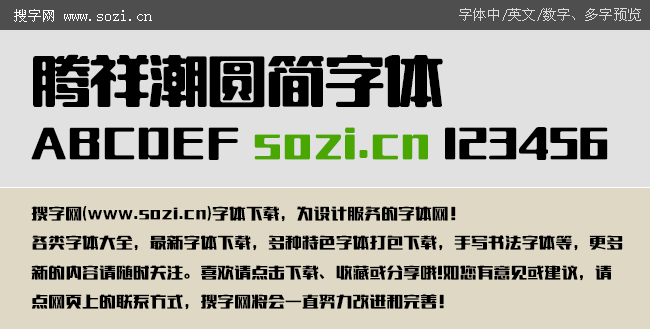
騰祥潮圓簡字體
搜字網(wǎng)提供一款騰祥潮圓簡中文藝術(shù)字體下載,潮圓是一款富于變化的美術(shù)類黑體,是在潮黑的基礎(chǔ)上變換設(shè)計(jì)而成。雖然字形結(jié)構(gòu)與潮黑相同,但兩款字的風(fēng)格氣質(zhì)截然不同。潮圓將潮黑的棱角柔化形成被融化之感,融化了的筆畫圓潤富于親和力。字形結(jié)構(gòu)扁方、端莊,橫豎筆畫粗細(xì)比例適度、豎筆粗壯有力,布白均勻、行文貫通。潮圓筆畫簡潔圓潤細(xì)微處變換靈動,即實(shí)用又富有裝飾效果。適合標(biāo)題用字,可用于印刷出版、包裝設(shè)計(jì)、廣告設(shè)計(jì)、網(wǎng)頁設(shè)計(jì)等。